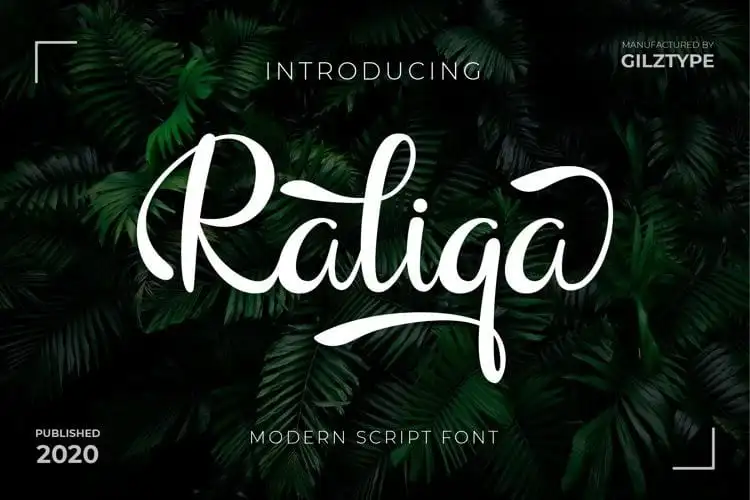
Raliqa Calligraphy Font – Fonte Grátis
Raliqa Calligraphy Font
A Raliqa Calligraphy Font é uma fonte que combina encanto antigo com modernidade sofisticada. Suas linhas elegantes e detalhes suaves oferecem um equilíbrio perfeito entre a estética clássica da escrita calligráfica e as características contemporâneas presentes em muitos tipos digitais atuais. Seu design é tão rico em detalhes que permite alternativas de caracteres e ligaturas, adicionando ainda mais personalidade e originalidade ao seu projeto. Não à toa, esta fonte foi projetada pela Gilz Type, um designer conhecido por criar soluções visuais únicas e inspiradoras. Raliqa é perfeita para qualquer projeto criativo, desde a criação de logotipos e rótulos até a produção de embalagens e estampas, oferecendo uma maneira elegante e única de expressar sua marca ou ideia.